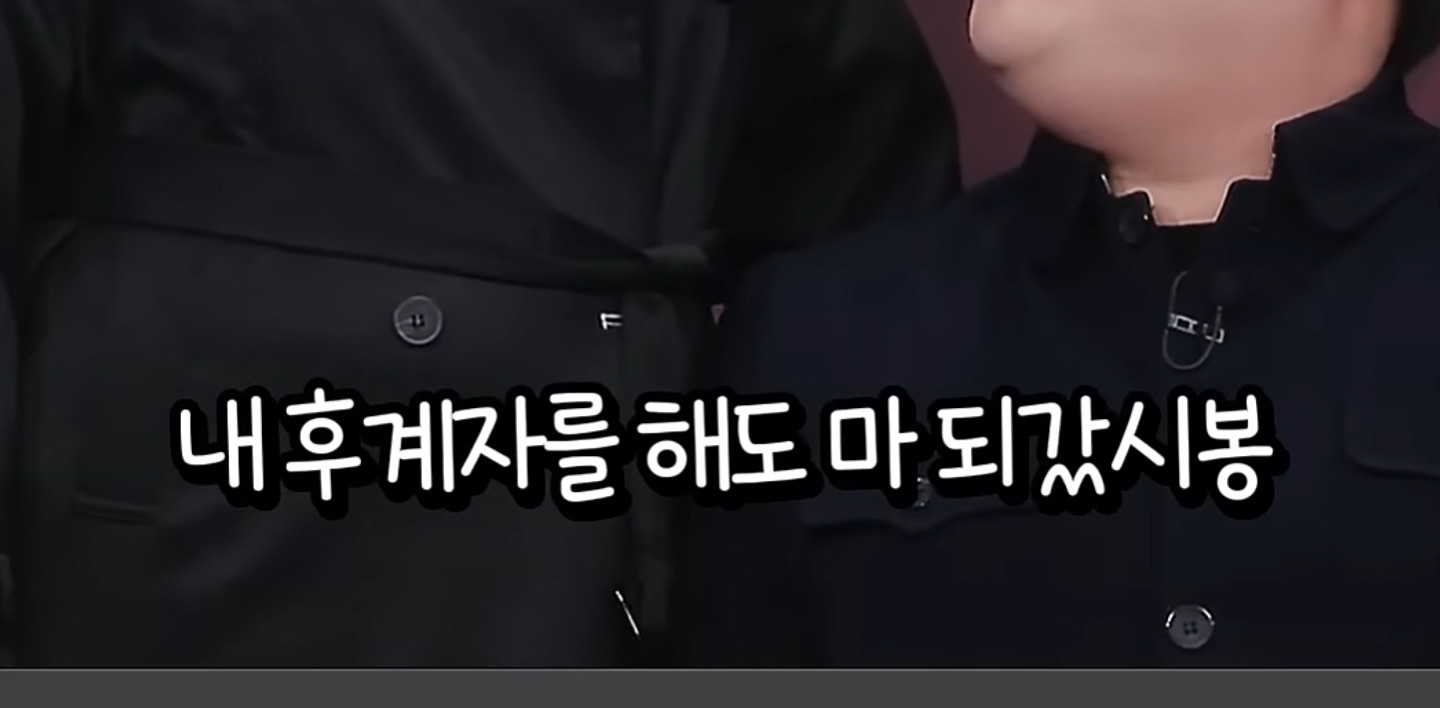
수박양체
Watermelon Yang
作成者 Watermelon X Fontrix
スタイル 手書き
私の手書きフォントをデザインした「スイカちゃん体」フォントが登場しました!<フォントリクス>が開発に尽力してくださいました!スイカちゃんとフォントリクスがコラボして制作されたスイカちゃん体は、すべて無料で利用できます:)